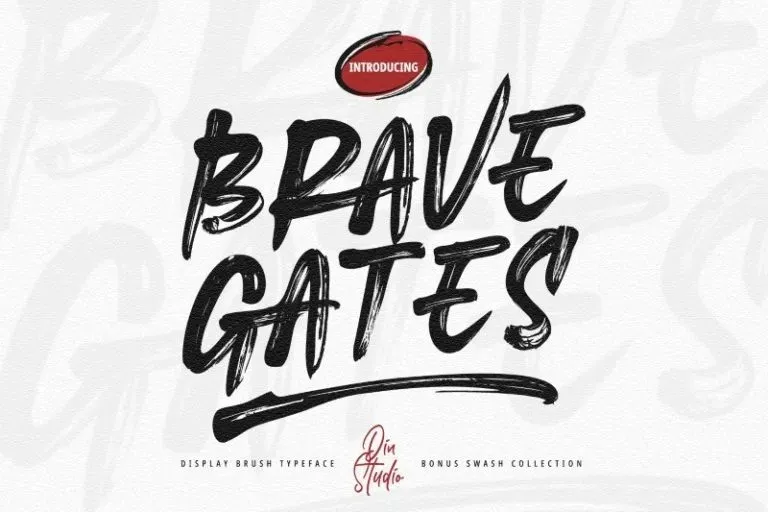
A “Brave Gates Font” é uma escolha perfeita para designers que buscam um estilo moderno e autêntico no seu trabalho. Criada pela Din Studio, essa fonte script está repleta de swashes, traços e curvas meticulosamente criadas para entregar aquela sensação de felicidade e elegância que é tão valorizada atualmente. Ela tem um toque moderno de uma varal, mas não perde a essência pessoal e arrojada. Este design bold é ideal para qualquer projeto que busque uma expressão independente e direta. Não importa se você está trabalhando em designs de site, ilustrações ou apresentações – essa fonte tem o poder de transformar seu trabalho digital com um toque único de personalidade. Obrigado a todos os designers que estão sempre buscando novas maneiras de destacar suas criações. Com “Brave Gates Font”, você terá uma ferramenta valiosa para criar algo realmente especial e atrativo em seus projetos.